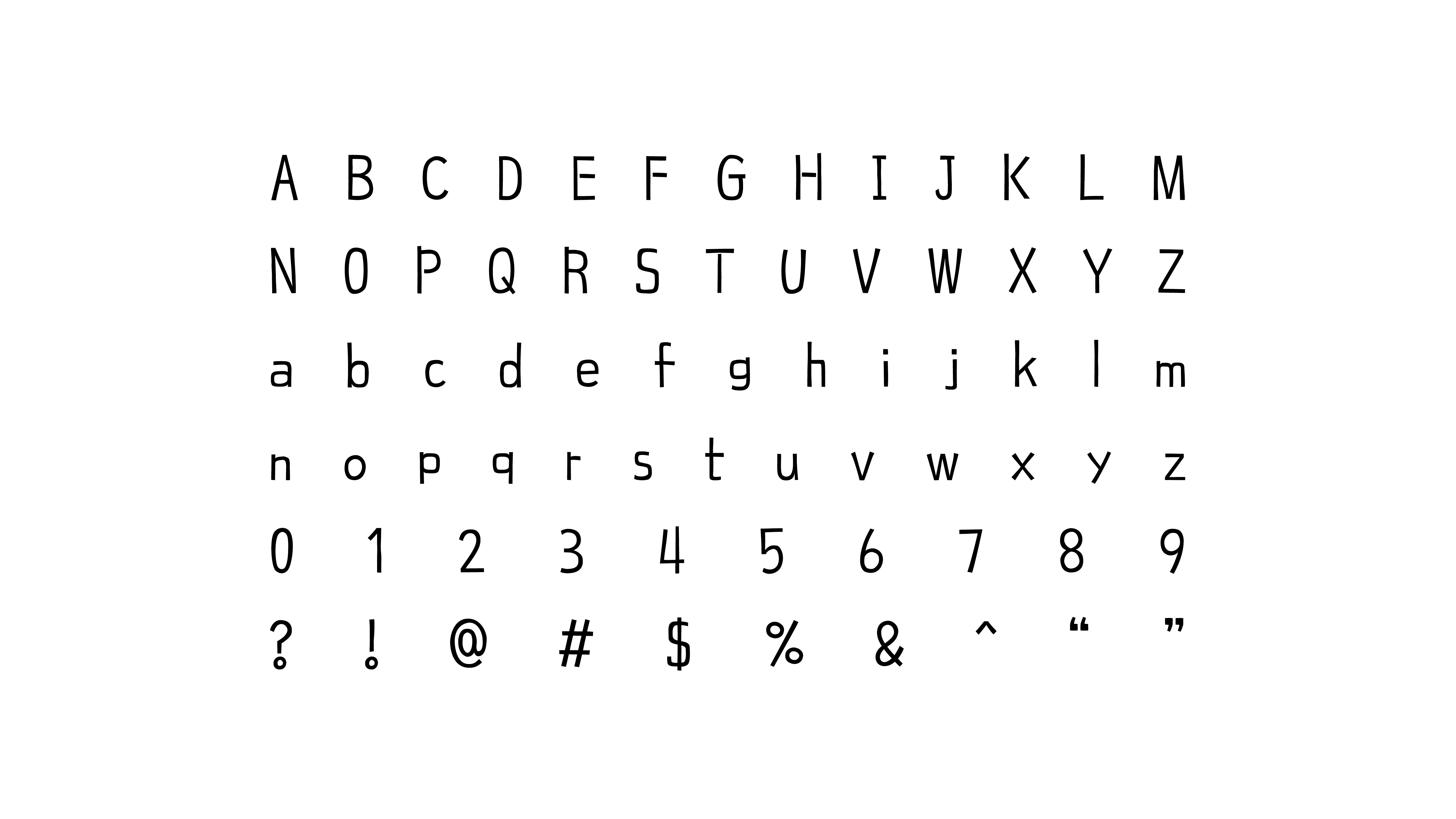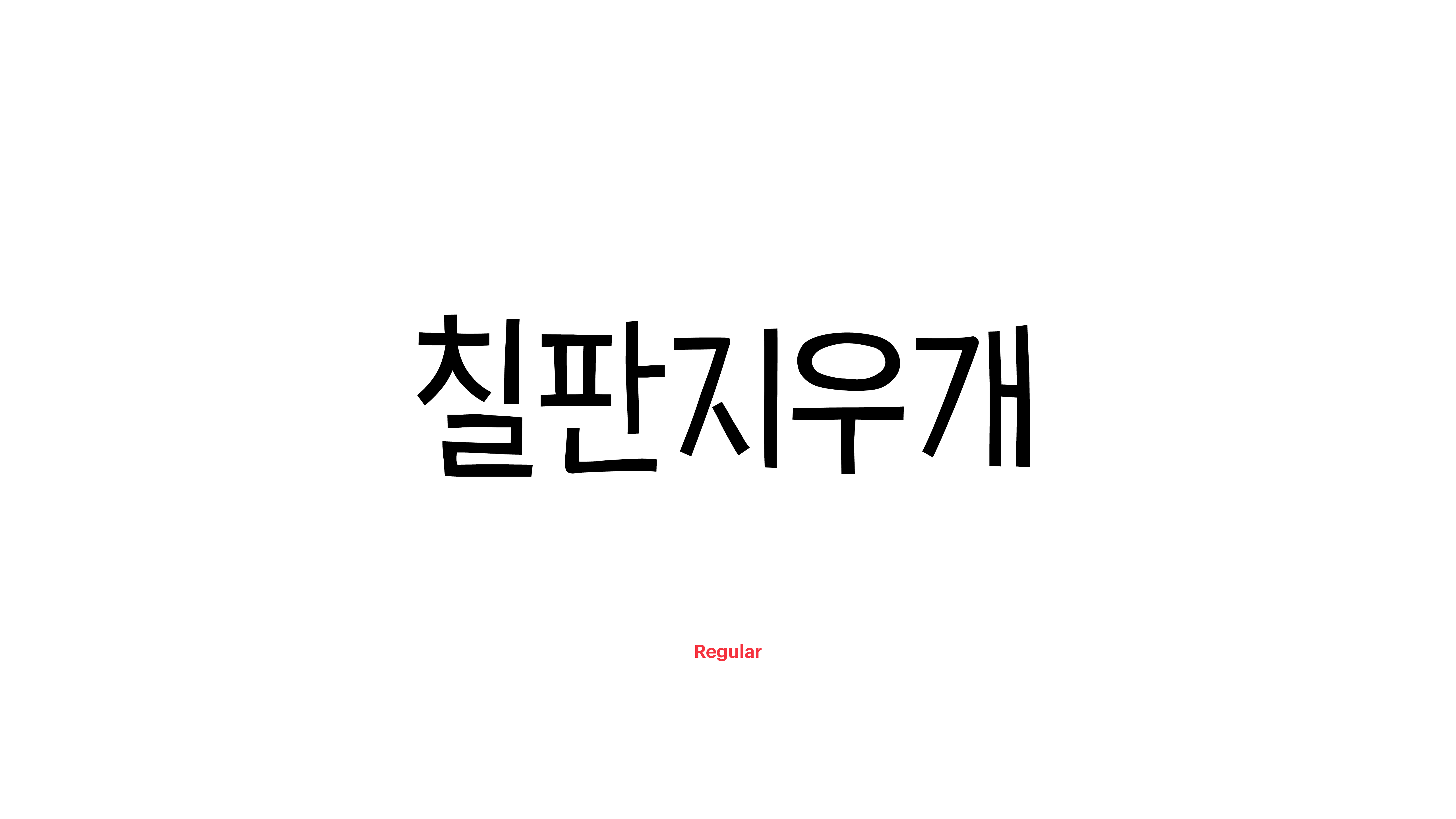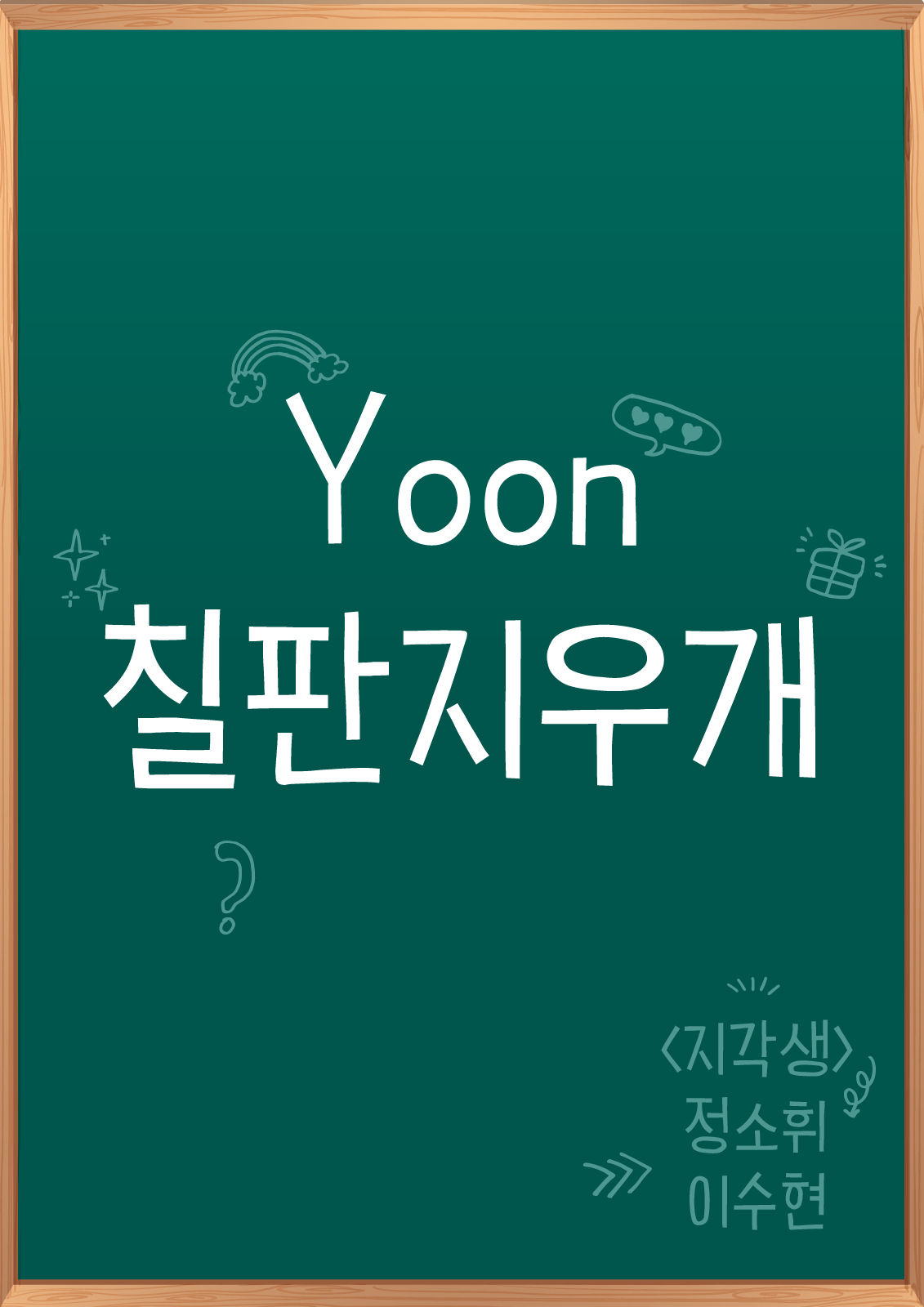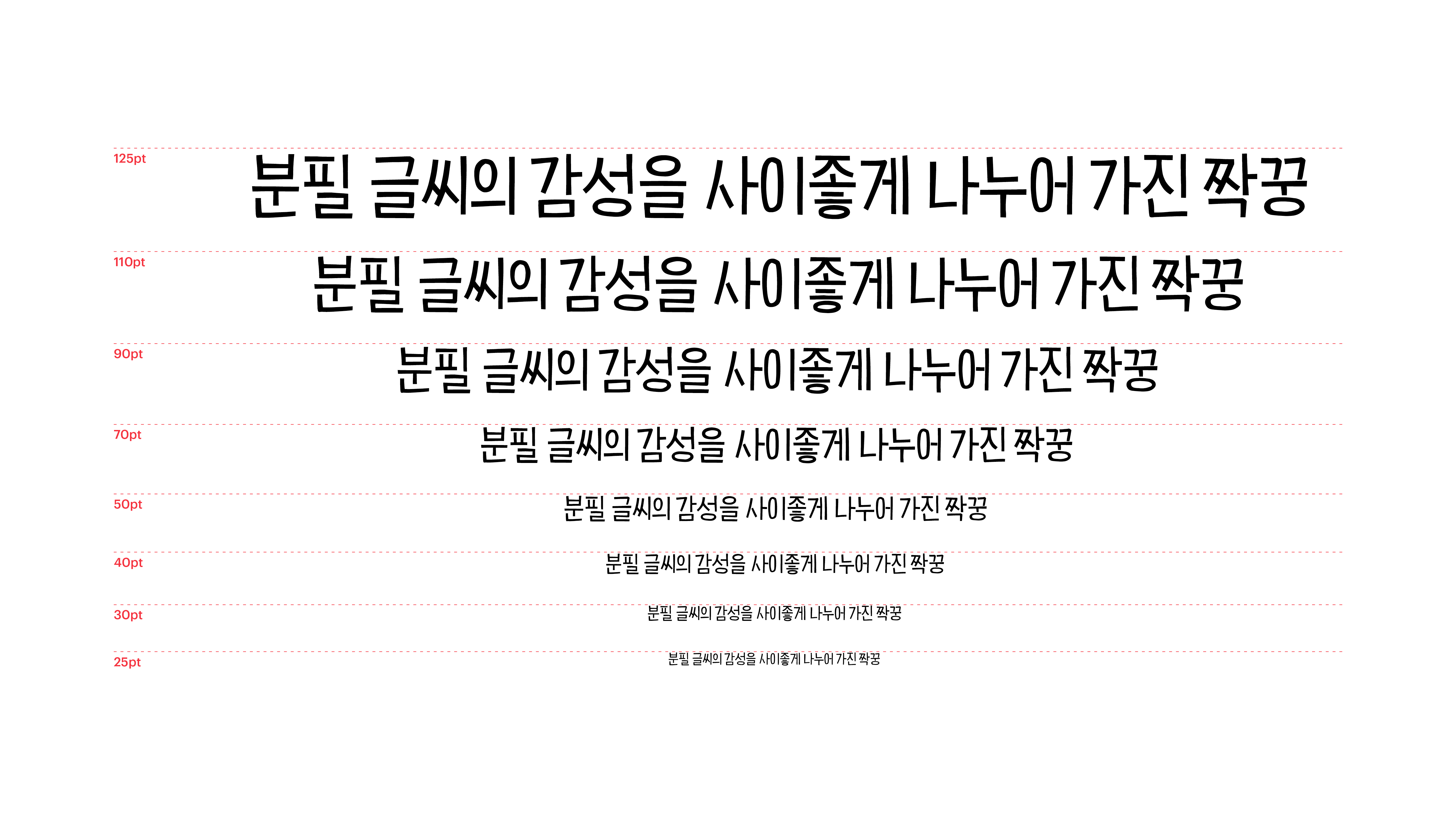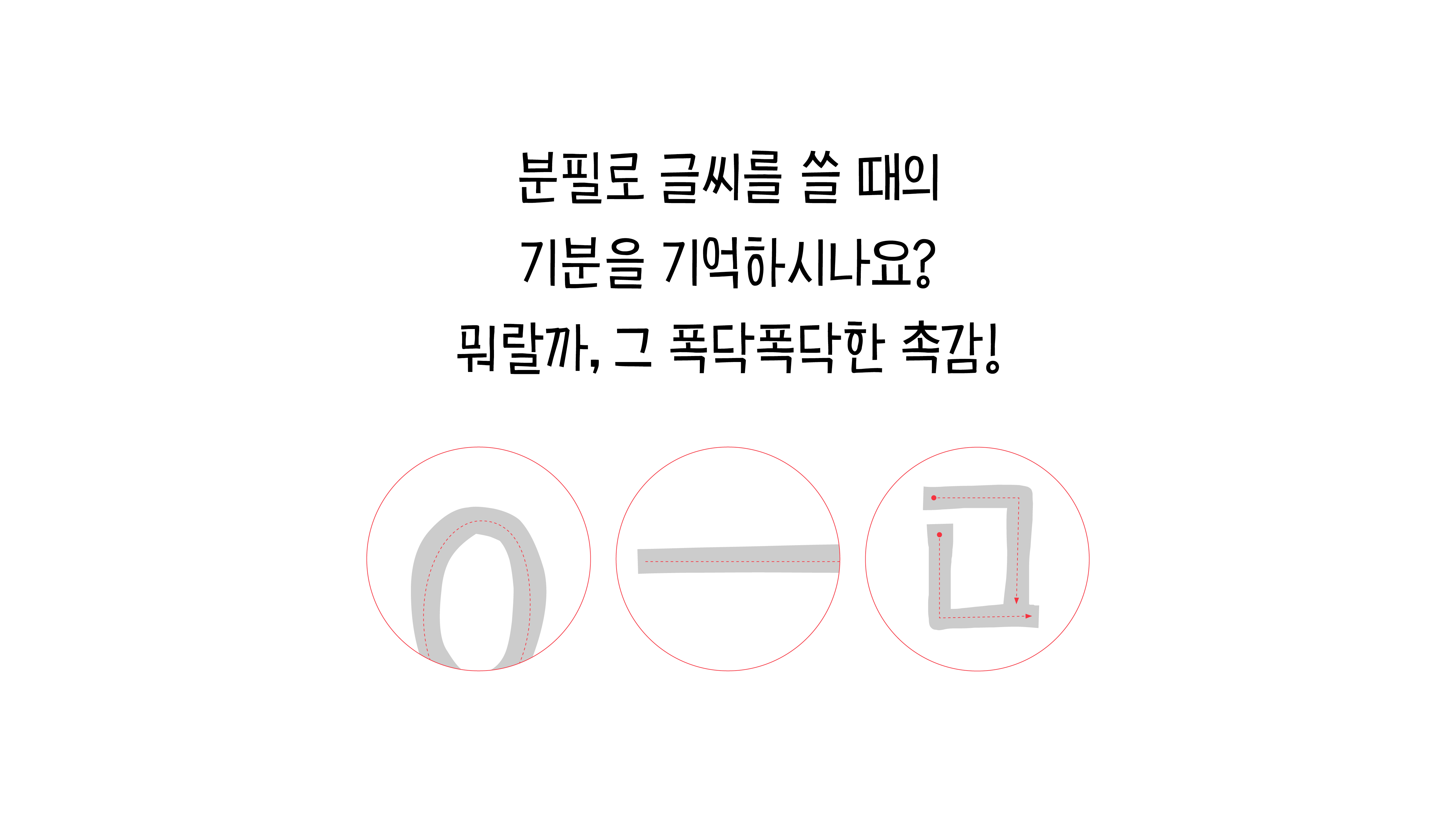
Yoon 칠판지우개
분필로 글씨를 쓸 때의 기분을 기억하시나요? 뭐랄까, 그 폭닥폭닥한 촉감! 칠판지우개체는 분필 글씨의 감성을 사이좋게 나누어 가진 짝꿍입니다. 또박또박 똑 부러지지만, 어쩐지 금세 지워질 것 같기도 한 아련한 정서를 전달하지요. 방과 후 칠판에 남아 있던 낙서처럼, 어쩐지 쉽게 지울 수 없을 것만 같은 이 폰트로 소중한 기억을 또박또박 적어보세요.